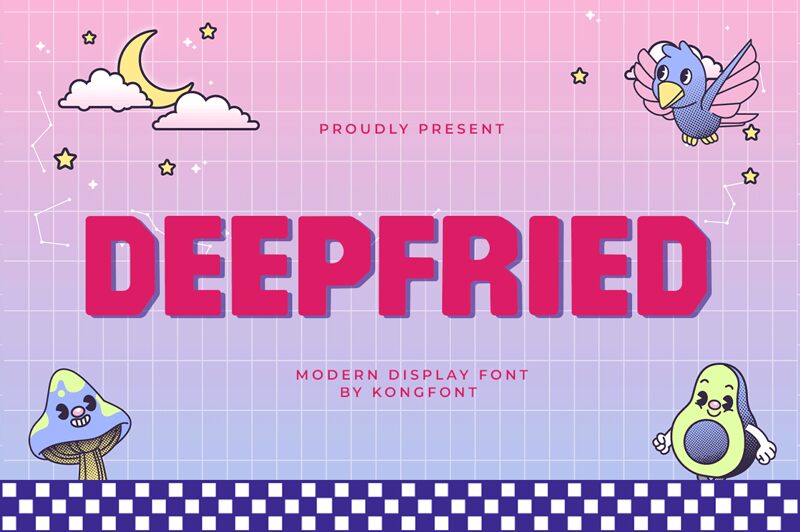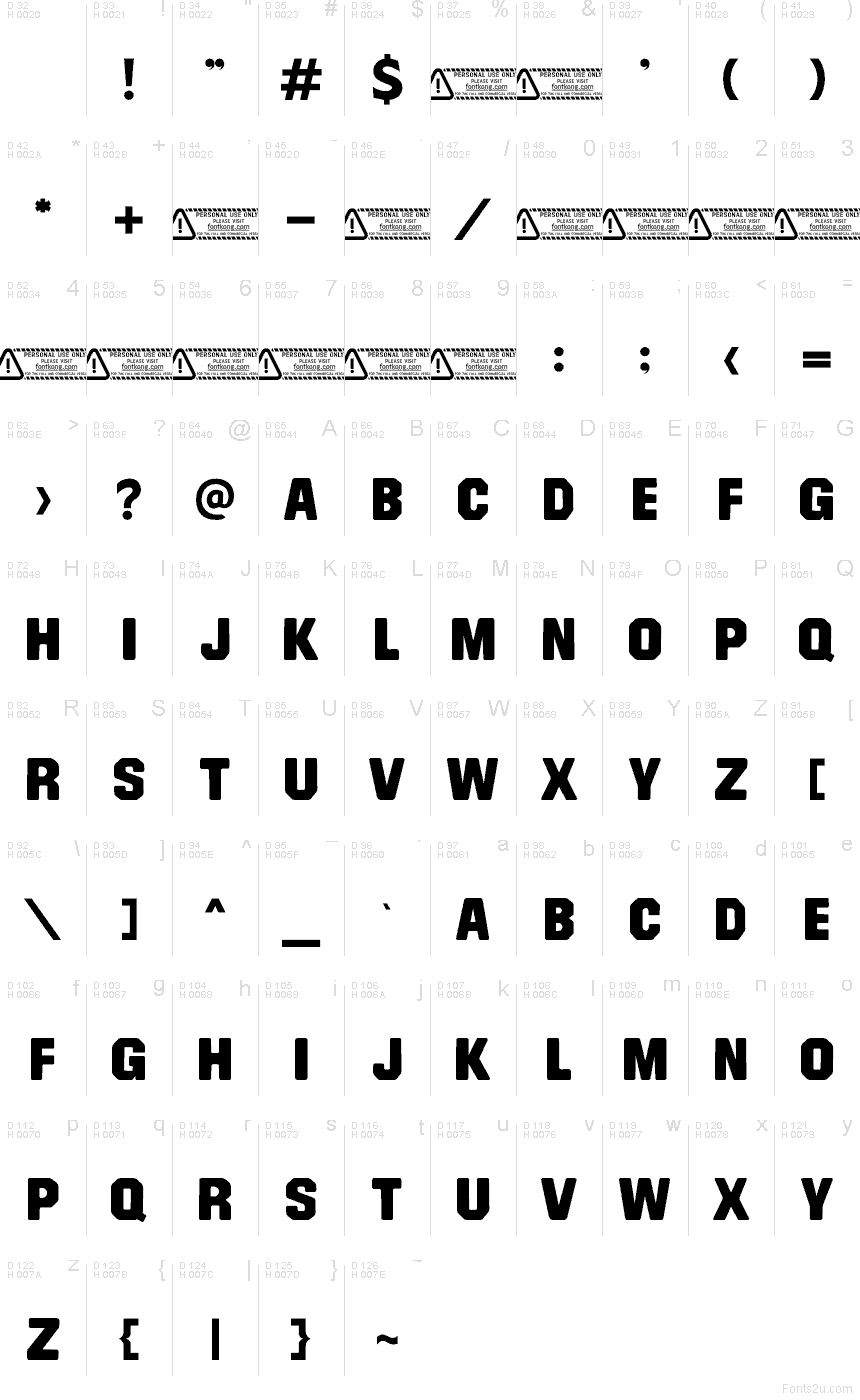
Deepfried ist eine kostenlose Old-School-Display-Schrift mit der rohen Wucht klassischer Arcade-Letterings. Die Großbuchstaben sind aus massiven, fast blockartigen Formen geschnitten, die quadratische Ecken mit breiten, kurvigen Aussparungen kombinieren – das lässt das Alphabet kompakt, laut und eher industriell als glatt wirken.
Durch diese Schwere eignet sich der Font perfekt für Poster-Überschriften, Gaming-Flyer, Streetwear-Designs, Cover-Layouts und Titelkarten, bei denen es auf einen harten Auftritt ankommt. Als Free-Font ist er zudem ideal für Logo-Entwürfe und kurze Brandings, besonders wenn Sie nach wuchtigen Formen suchen, die sich eng stapeln lassen und einen stabilen, direkten Rhythmus bewahren.